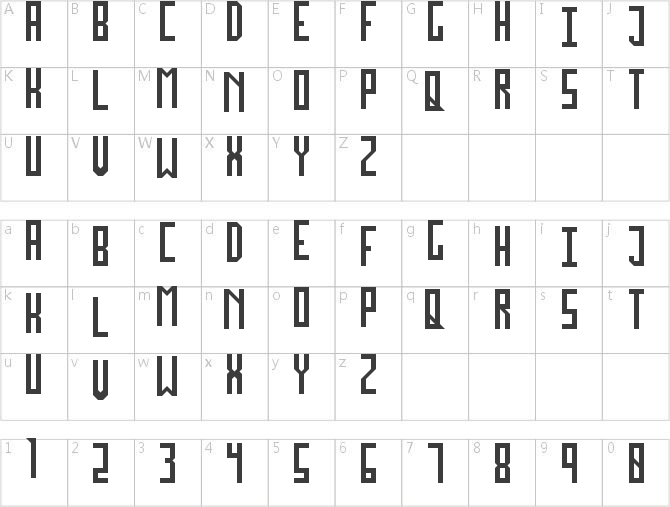
Jacko-Mongo-Regular 詳情頁
Jacko-Mongo-Regular字體字庫是一款讓人賞心悅目、百看不厭的英文字體,適合各類廣告和產(chǎn)品包裝設(shè)計(jì)應(yīng)用,字體大小0.01MB,格式為ttf字體,上傳用戶是韓國(guó)露韓,作者/版權(quán)方為未知